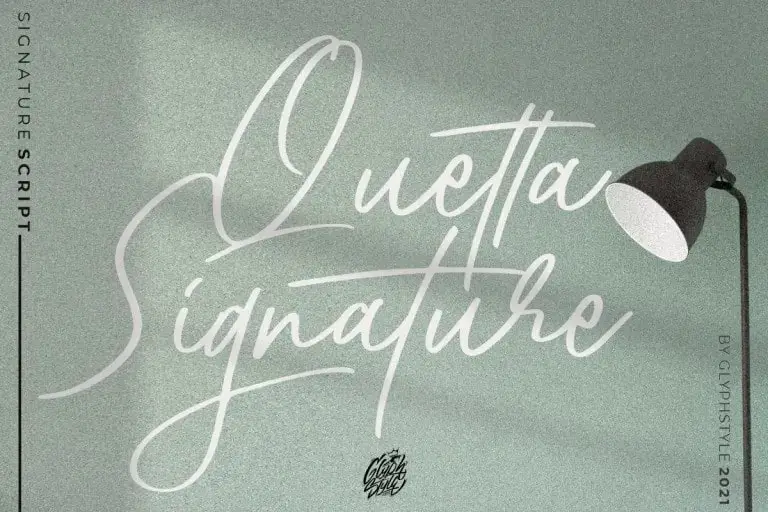
Quetta Script Font – Download Grátis
A Quetta Script Font é uma elegante tipografia escrita a mão que se destaca por oferecer um toque sofisticado aos seus designs. Criada pelos mestres do Glyphstyle, esta fonte é perfeita para aqueles que buscam um elemento único e diferenciador em suas criações visuais. Suave e fluida, ela pode ser usada em uma variedade de aplicações, desde assinaturas, logotipos, cards de convite até embalagens personalizadas. A Quetta Script se destaca não apenas pelo seu design gráfico refinado, mas também pela sua capacidade de dar um ar especial a qualquer projeto que ela encontre. Seja para uma marca ou uma empresa, é perfeitamente adaptável para criar um visual único e memorável. Para aqueles procurando por mais do que simples letras, esta fonte oferece precisão em misturar elegância com personalidade, tornando-a uma escolha ideal para designers e criativos de todo o mundo.